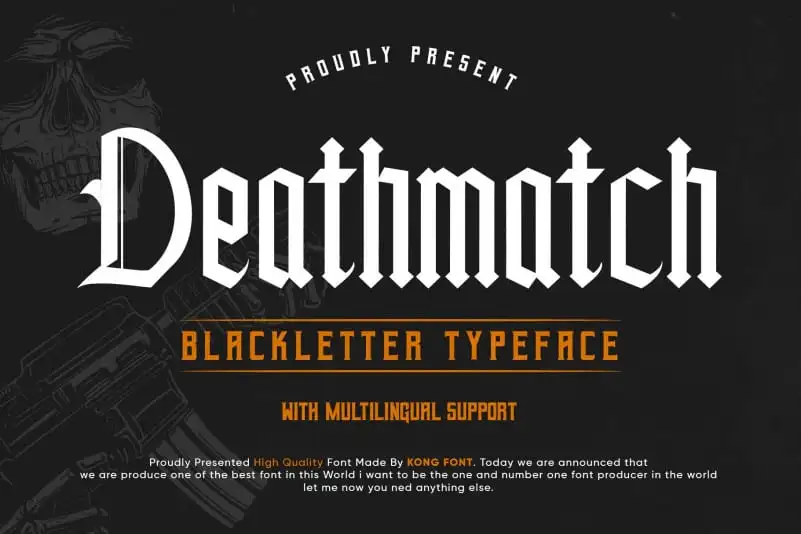
Deathmatch Display Font – Download Grátis
Deathmatch Display Font é uma fonte Blackletter que traz a autenticidade característica dos gírias verbais do passado nas palavras. Com seu contraste único e presença forte, esta fonte é perfeita para designers de todos os níveis, seja você criando um logotipo moderno ou um desenho infantil. Ideal para uso em variados formatos de design, desde cartazes e letras do quote até editoriais e materiais personalizados como mug, camisa personalizada e até mesmo decoração com letras a mão. Este font foi criado pelo fontkong na 99designs, uma plataforma popular entre designers. Suas linhas sóbrias e detalhes incertos trazem um toque nostálgico e original que é perfeito para destacar seus projetos de design. É uma escolha ótima para aqueles buscando algo diferenciado para suas criações, seja ela impressa ou digital. Neste universo dinâmico do design gráfico, a Deathmatch Display Font oferece um ponto focal único e inconfundível, garantindo que sua marca seja lembrada. Seja você criando material para uma campanha publicitária moderna ou desenhando o próximo sucesso infantil, esta fonte é certamente a escolha perfeita.